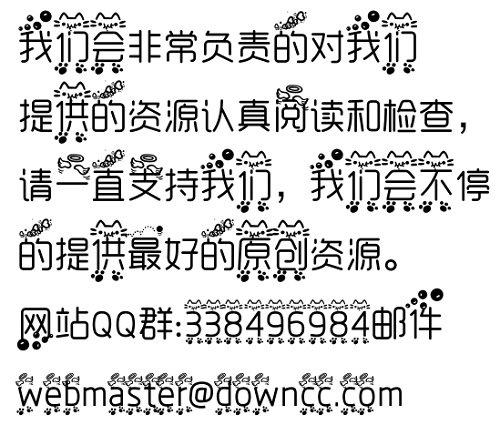
泡泡貓貓字體ttf
泡泡貓貓字體是一款非??蓯叟菖莺拓堖鋱D案的卡通字體,讓你的文字更加更加有樂趣和兒童趣味,喜歡的朋友就來綠色資源網(wǎng)體驗(yàn)吧!
貓貓字體ttf特色
泡泡貓貓字體并未將所有的文字變成好看的卡通造型,而是在文字的周圍增加了可愛的桃心、棋牌、貓爪印等圖案,讓文字變得更加溫順乖巧,討人喜歡。
泡泡貓貓字體兼具藝術(shù)字體pop字體的美感和特色,給人韻味十足的活潑體驗(yàn),漫畫風(fēng)格的點(diǎn)綴讓你的文字更加生動活潑,適用在藝術(shù)設(shè)計(jì)、平面設(shè)計(jì)等行業(yè)。